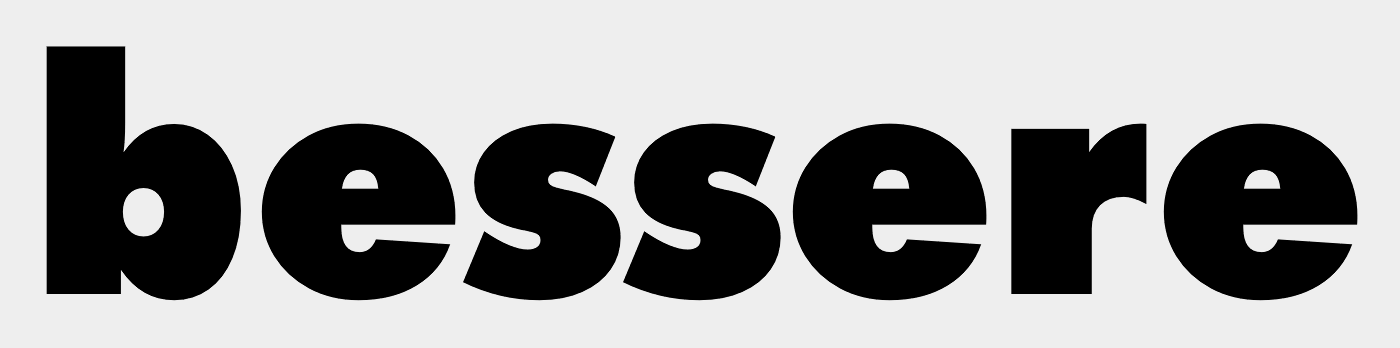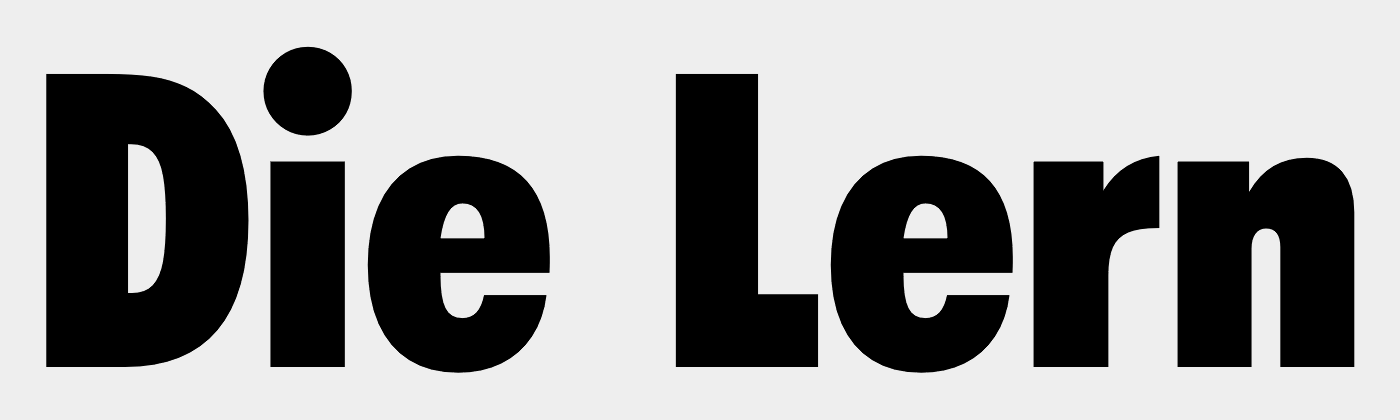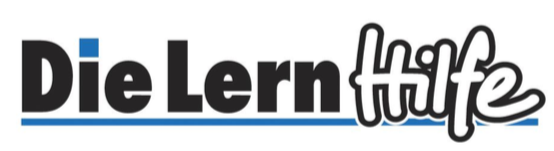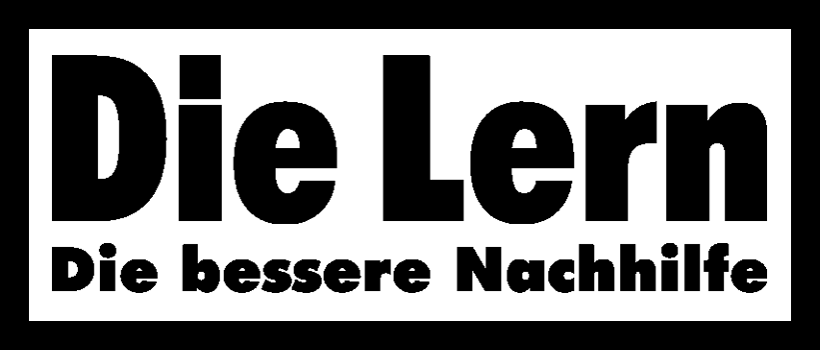
Suche Schriftart aus Logo von Die Lernhilfe
ich suche ganz dringend die Schriftart aus diesem Logoteil. Mehr Infos dazu habe ich leider nicht, nehme aber an beim oberen Teil es handelt sich wohl um die Condensed-Version eine bekannten Font. Vielleicht sogar die gleiche Font wie unten?
Sieht auch nicht besonders gut aus.
In Farbe geht’s so …